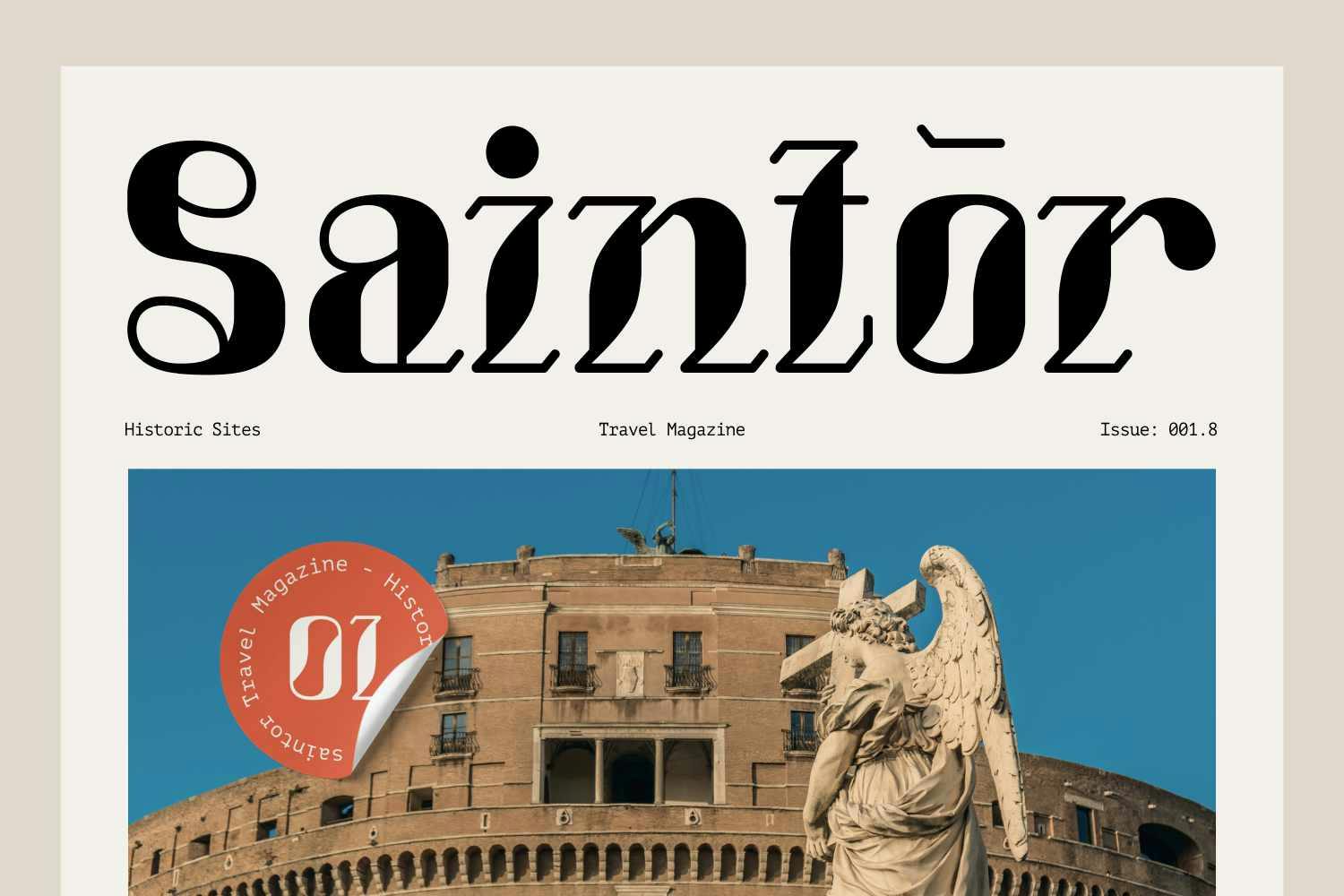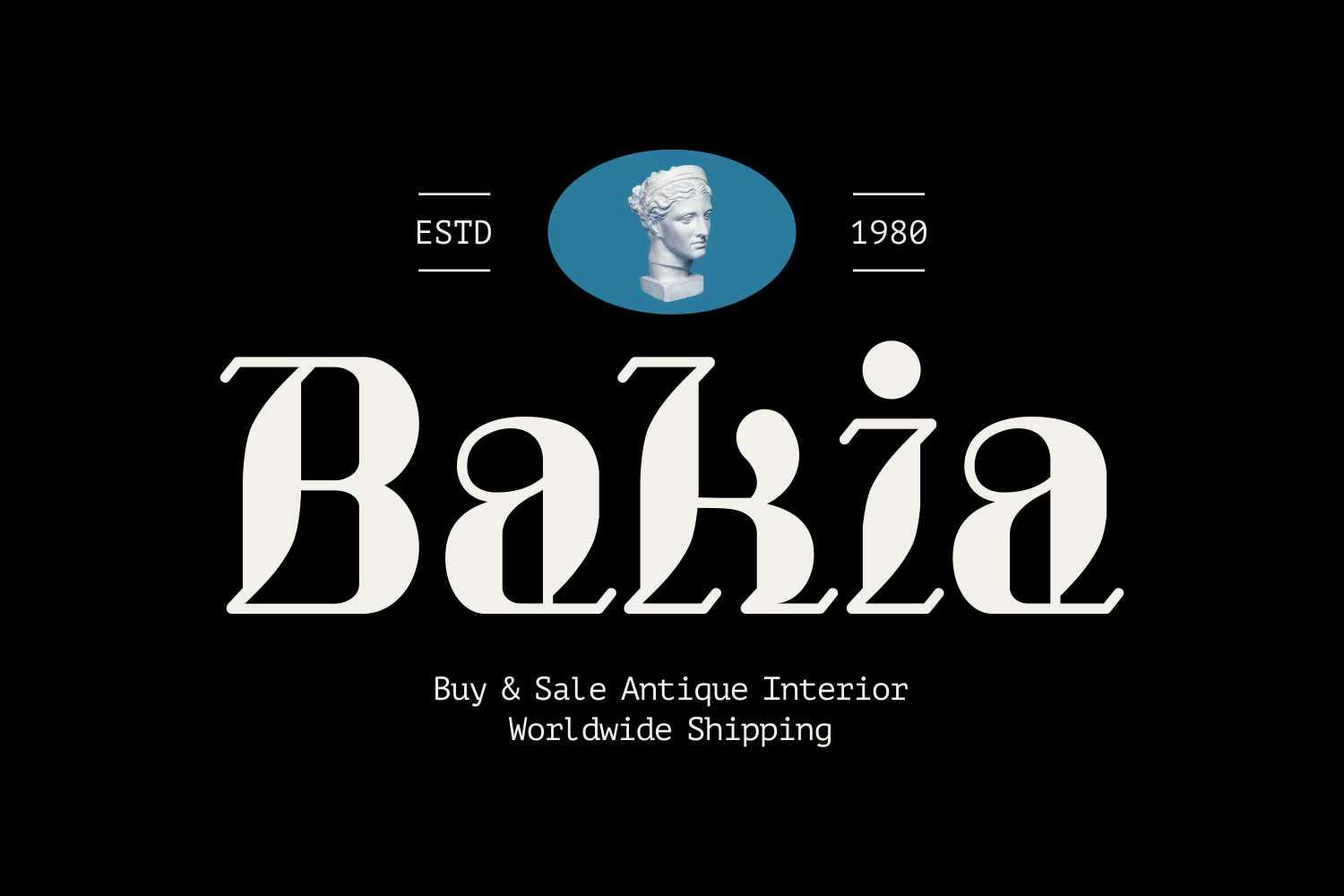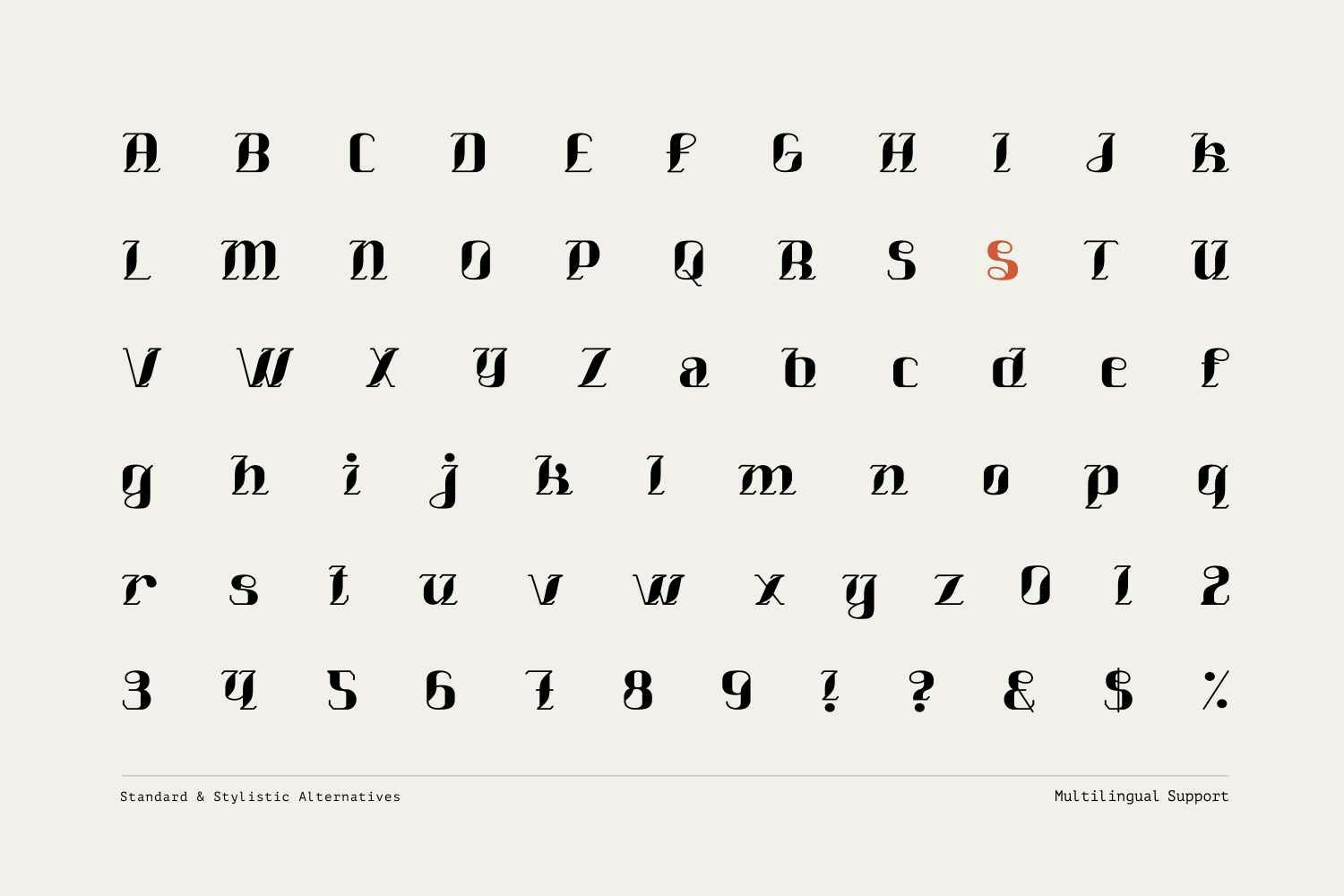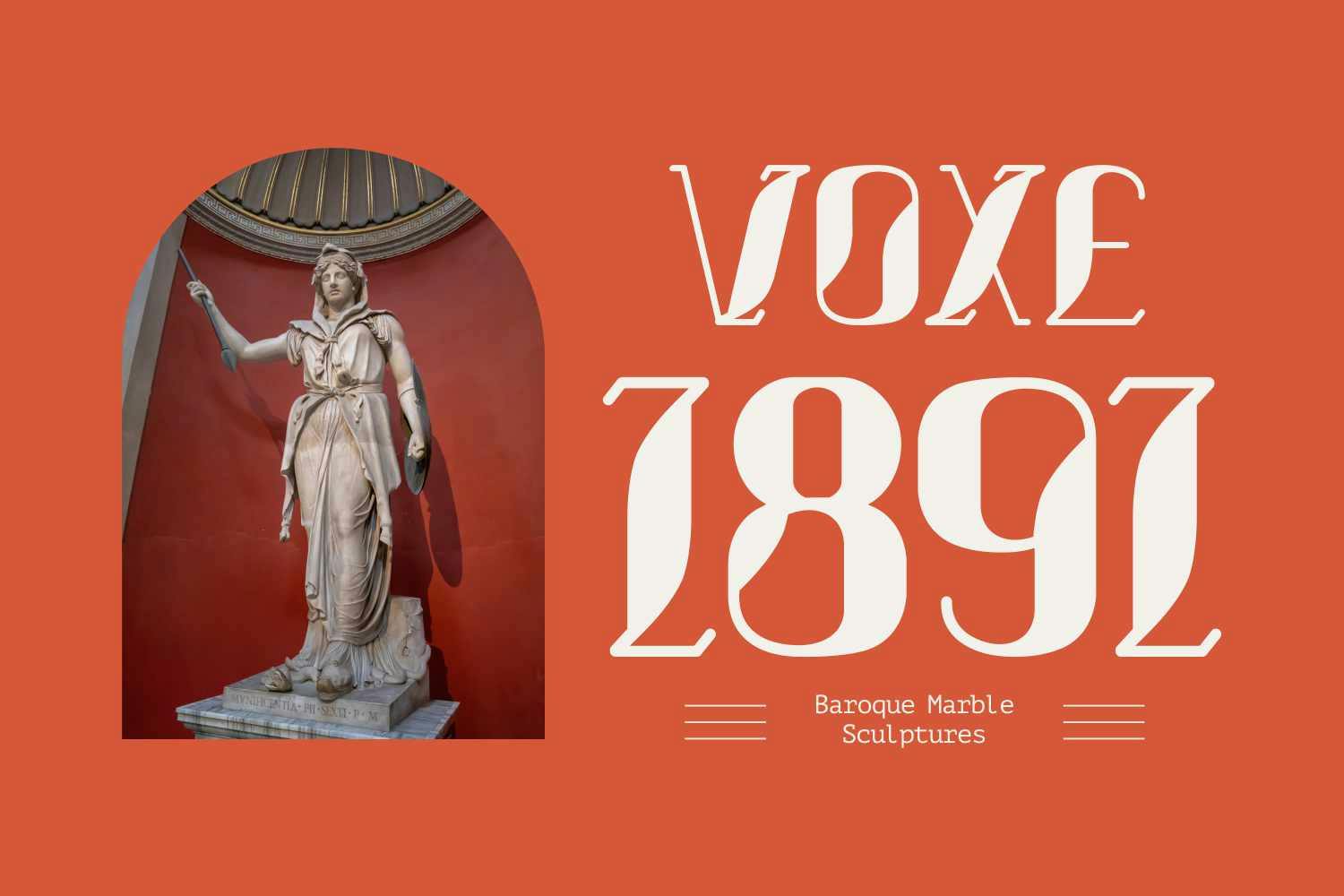
معرفی فونت Vodigl، فونتی مناسب برای برندینگ، کتاب، لوگو، مجله، محصولات مد، نقلقولها، پوستر، و سرعنوانها و غیره است. این فونتها شامل حروف بزرگ و کوچک، اعداد و نشانهگذاری، پشتیبانی چند زبانه و ویژگیهای OpenType میباشند. برای طراحیهای شگفتانگیز میتوانید از ترکیب این فونت با دیگر فونتها به عنوان مکمل استفاده کنید.